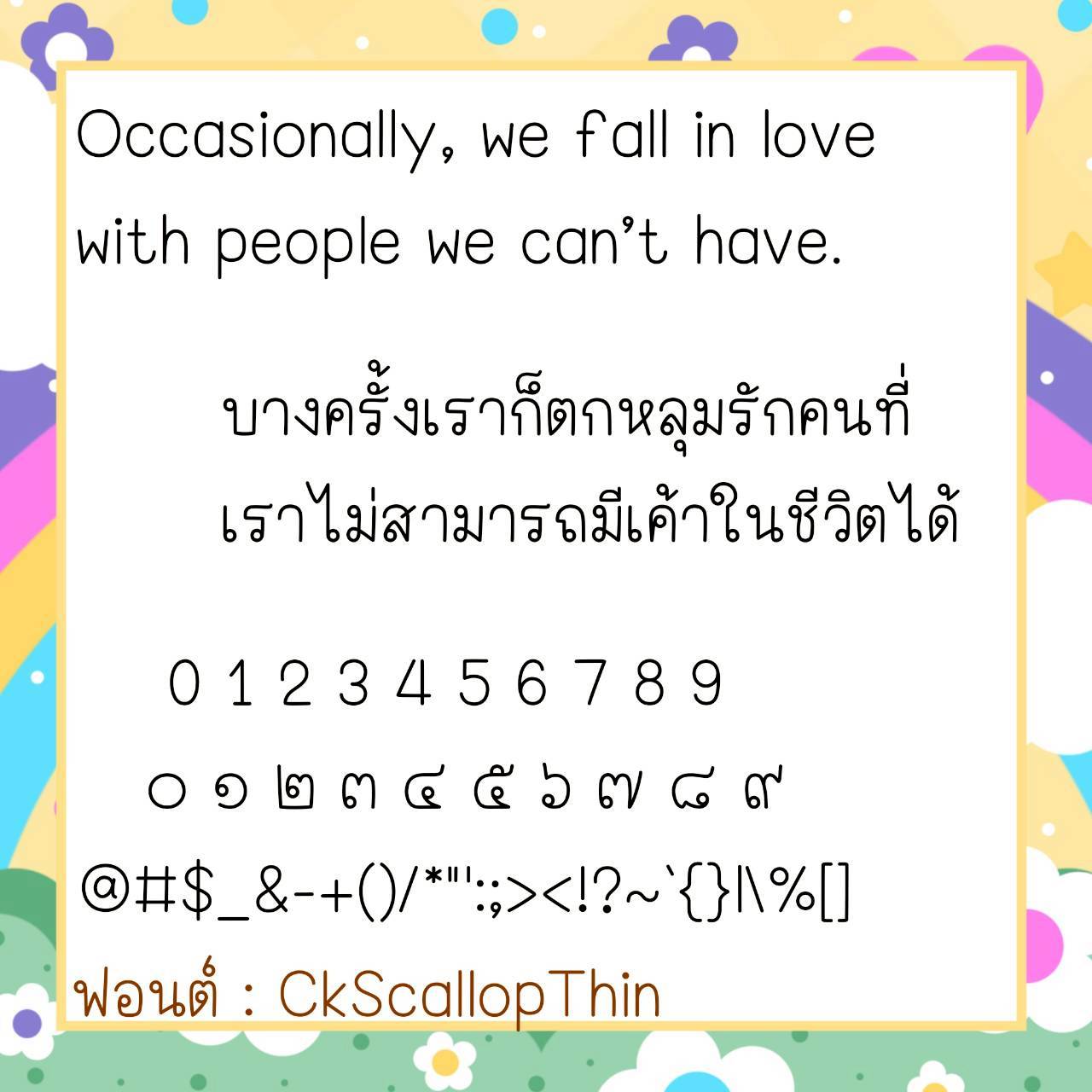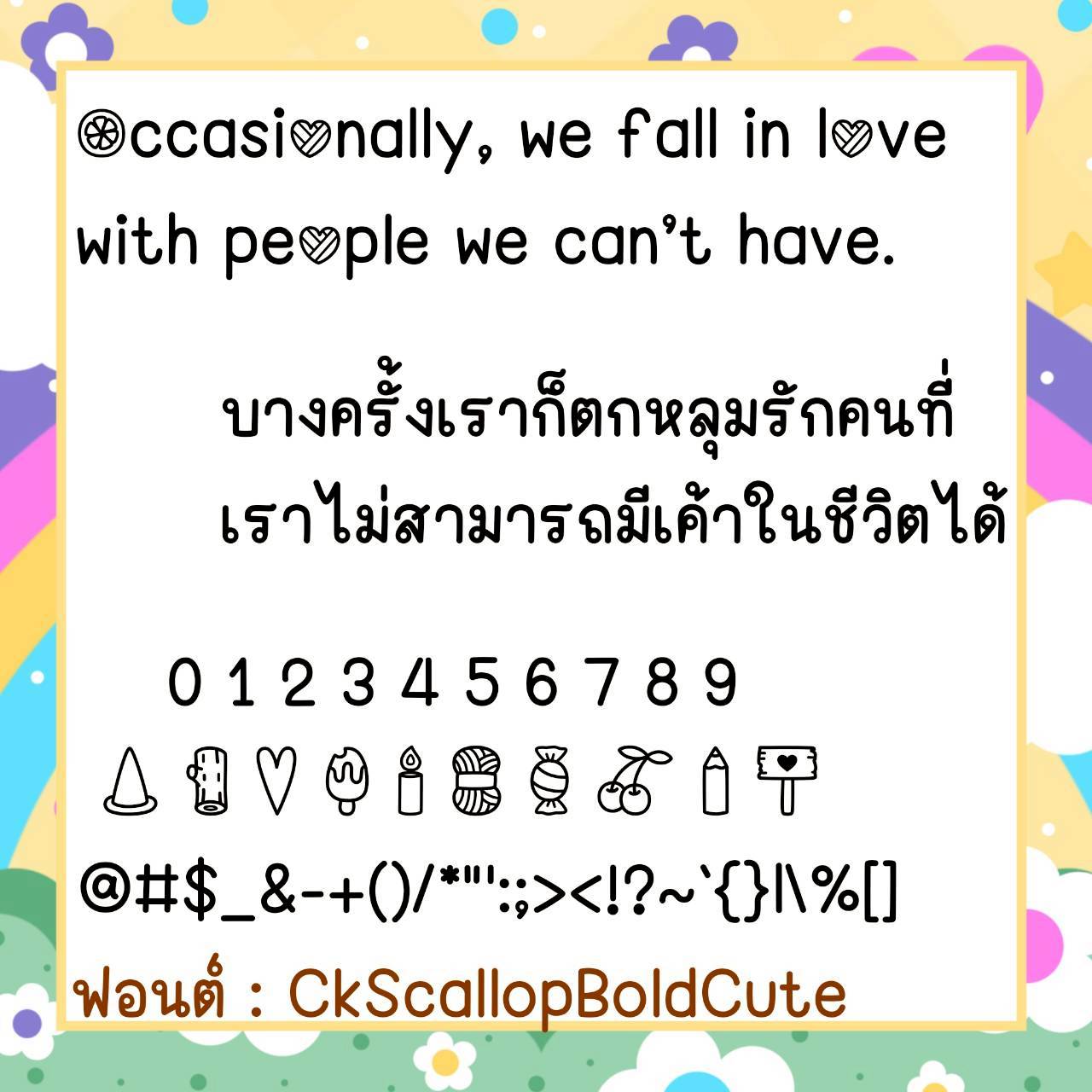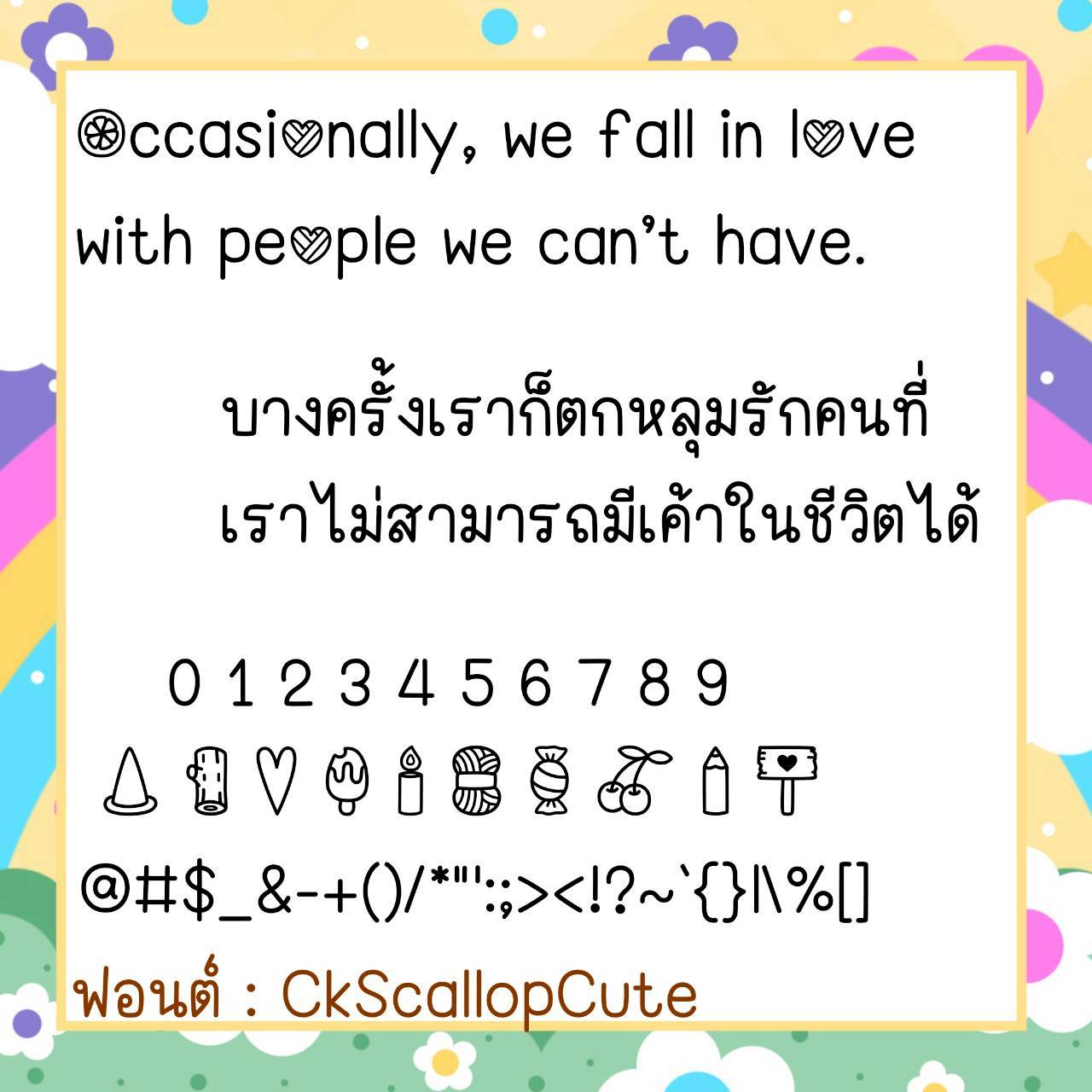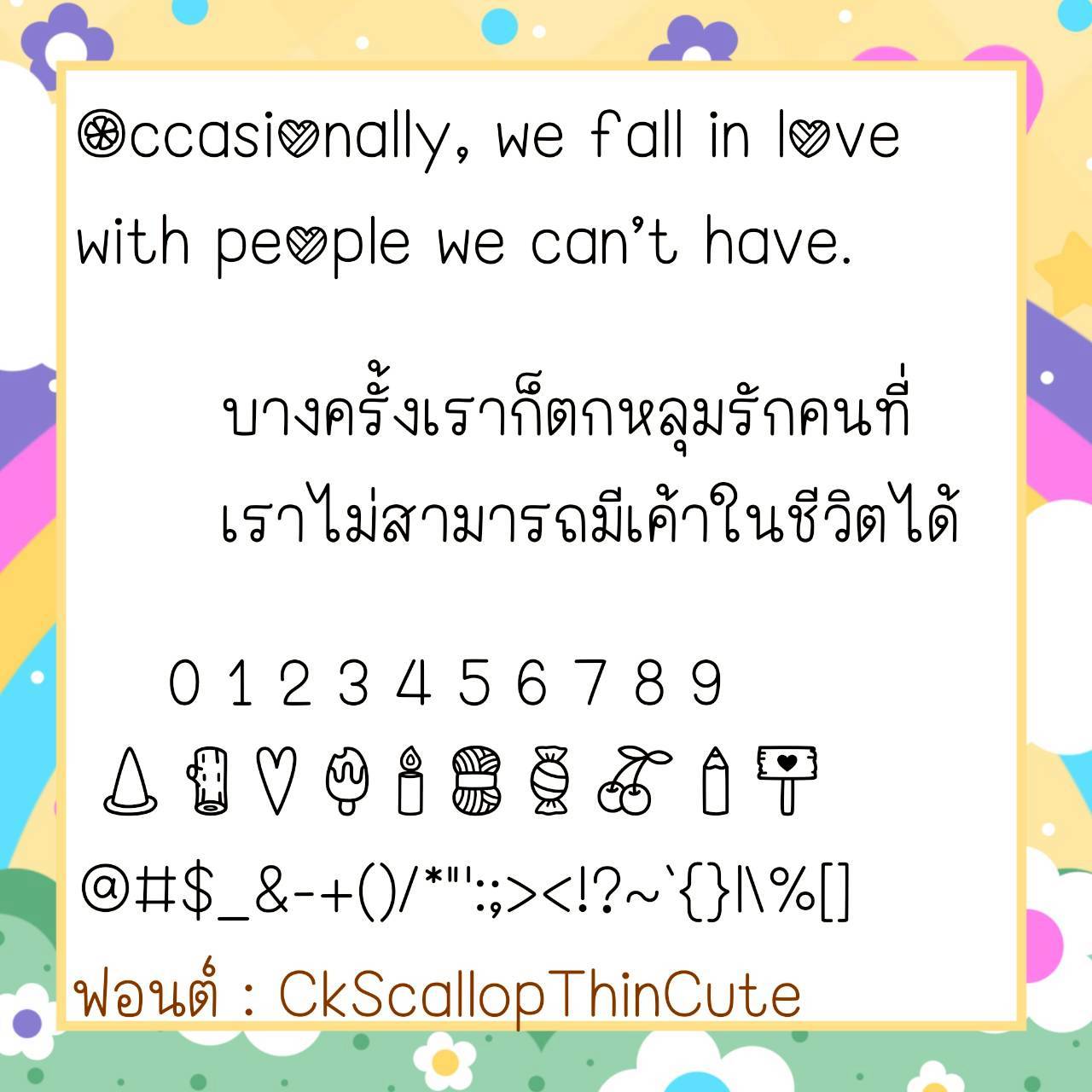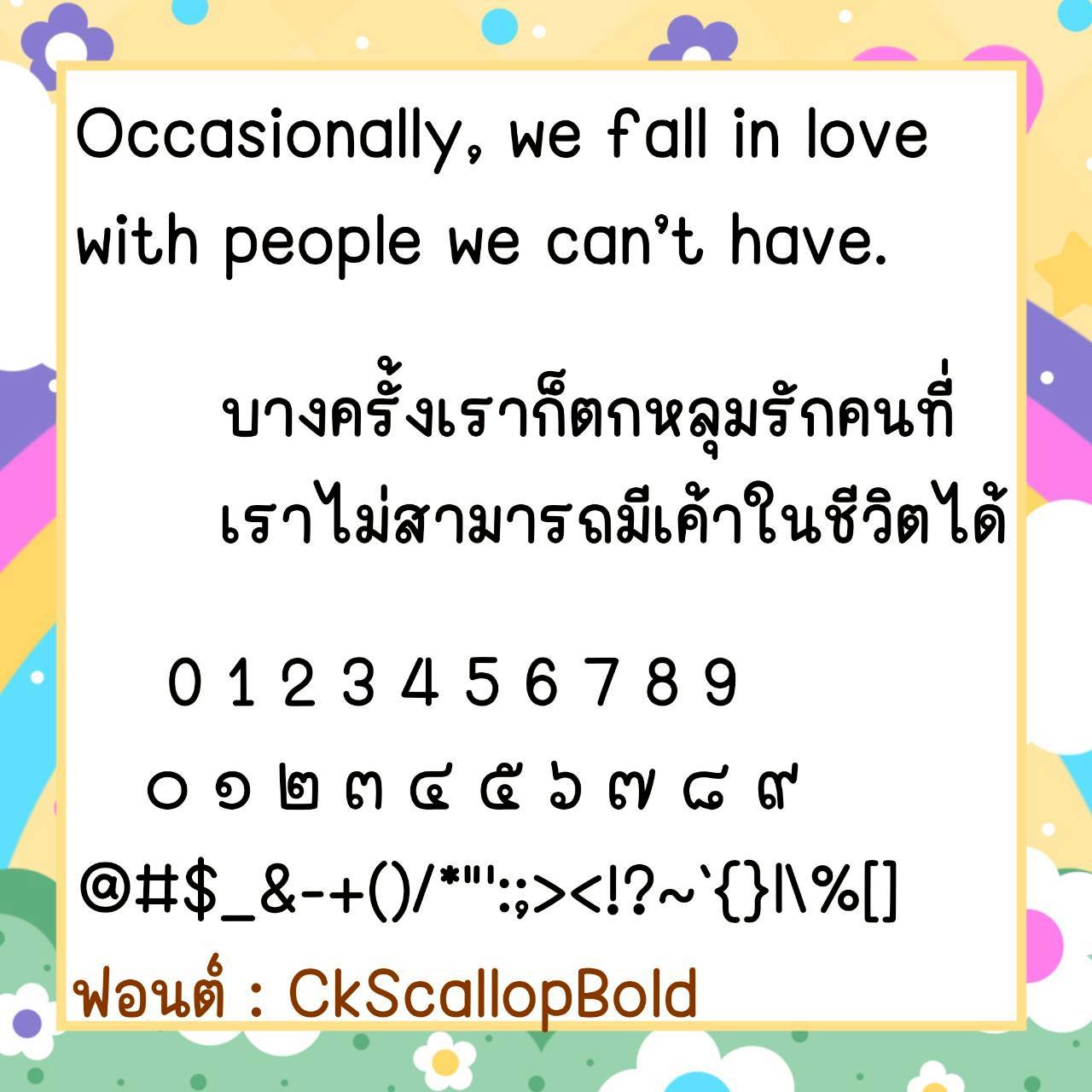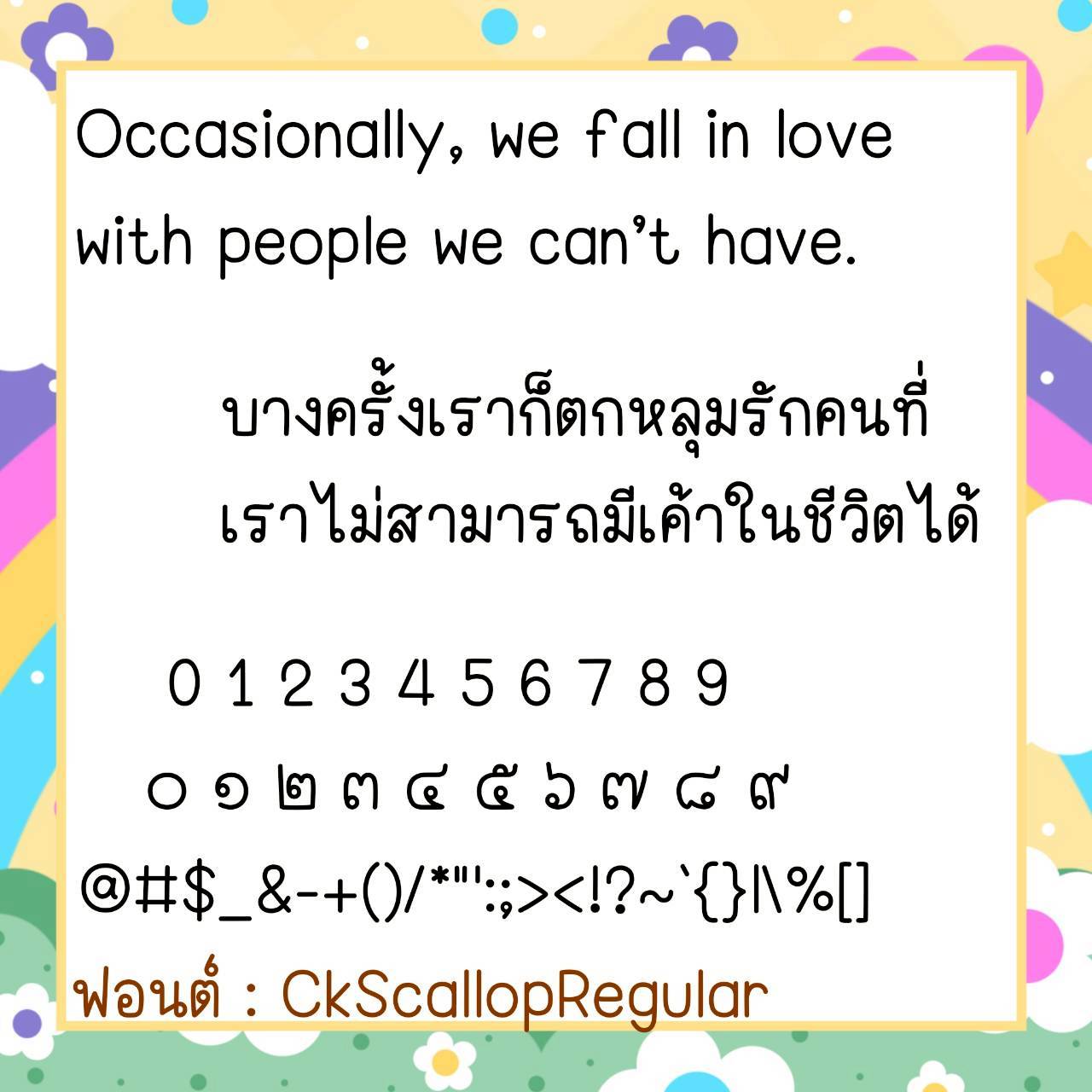
Font CkScallop
🔸 ฟอนต์ลายมือแนวเรียบร้อย ขนาดฟอนต์กำลังพอดี เน้นความเป็นระเบียบดูดี อ่านง่าย และยังมีไฟล์อิโมจิน่ารักๆที่ใช้แทนเลขไทยให้ด้วยค่ะ 🥰💙
🔹 A neat, handwritten font with a comfortable size, emphasizing orderliness, a professional look, and ease of readability. It also includes cute emoji files to replace Thai numerals. 🥰💙